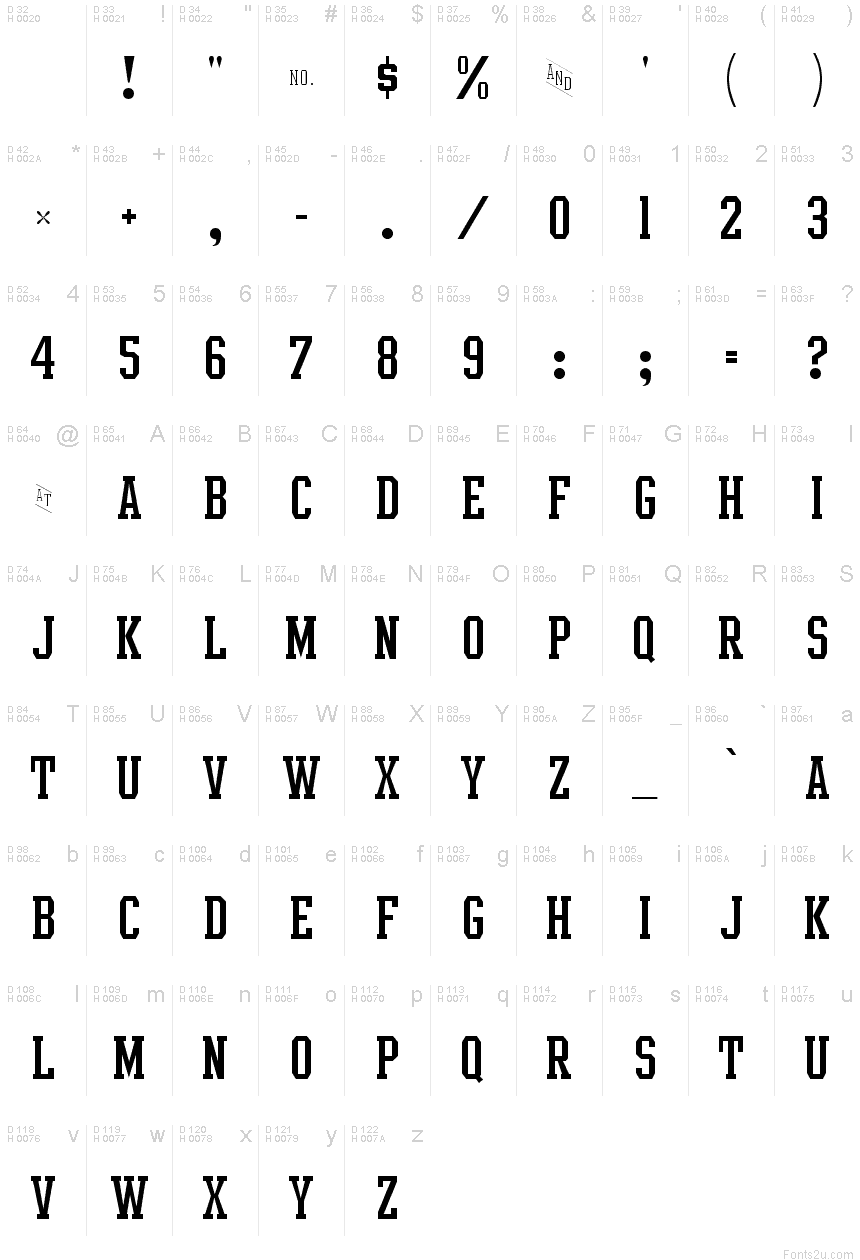
Intramural JL von Jeff Levine & Ray Larabie ist eine kostenlose, klassische Slab-Serif-Schrift. Ihre hohen, blockartigen Lettern, die kantigen Formen und kräftigen Serifen erinnern an traditionelle Sportbanner und aufgestickte Trikotnummern – und verleihen jedem Wort diesen typischen Friday-Night-Lights-Vibe. Durch den festen, aufrechten Stand wirken die Zeilen wie Spinde in einer Umkleidekabine: selbstbewusst, gut lesbar und markant, ohne dabei zu wuchtig zu wirken.
Mit Intramural JL peppen Sie Sportplakate, Team-Logos, Branding für Sportvereine, Event-Flyer, Fanartikel und Vintage-Banner perfekt auf. Diese kostenlose Schrift kommt besonders groß und in Versalien zur Geltung, ideal in Kombination mit einer schlichten serifenlosen Schrift für begleitende Texte.
Intramural Light JL
Jeff Levine from a Ray Larabie original
A lighter weight version of "Intramural JL".